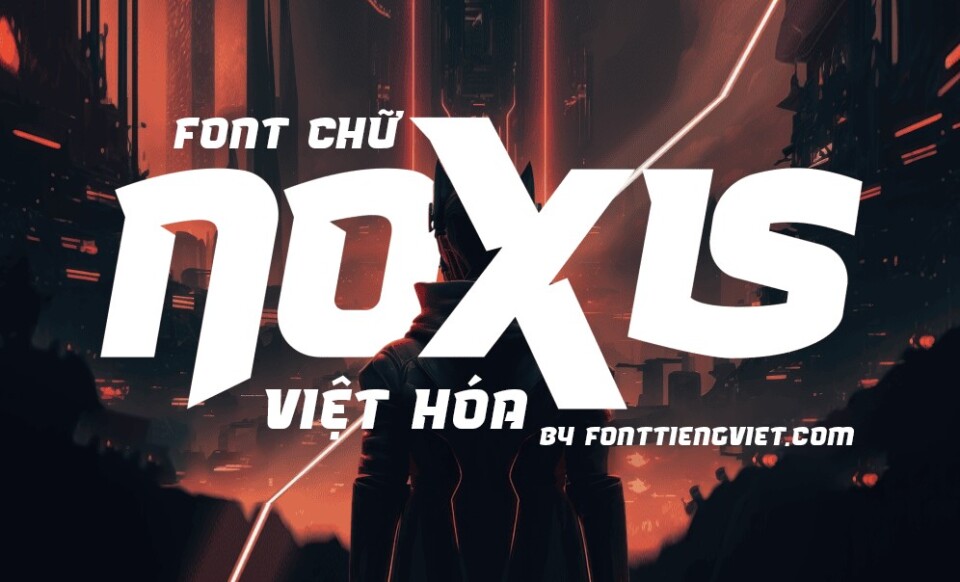
Font Việt hóa 1FTV Noxis
Giới thiệu bộ Font Việt hóa 1FTV Noxis đầy ấn tượng
Trong thế giới đồ họa hiện đại, việc tìm kiếm một Font Miễn Phí chất lượng và hỗ trợ tiếng Việt đầy đủ luôn là ưu tiên hàng đầu của các bạn học sinh cũng như giáo viên. Font Việt hóa 1FTV Noxis nổi lên như một sự lựa chọn hoàn hảo nhờ phong cách thiết kế mạnh mẽ, hiện đại và vô cùng chuyên nghiệp. Đây là bộ font mang hơi hướng tương lai, giúp các bài thuyết trình hay ấn phẩm truyền thông của nhà trường trở nên thu hút và dễ tiếp cận hơn với người xem ngay từ cái nhìn đầu tiên.
Đặc điểm nổi bật của Font Việt hóa 1FTV Noxis
Thiết kế tối giản và hiện đại
Font Việt hóa 1FTV Noxis sở hữu những đường nét thanh thoát nhưng không kém phần dứt khoát. Cấu trúc chữ được tối ưu hóa để giữ được độ sắc nét khi hiển thị trên cả màn hình kỹ thuật số lẫn bản in. Điều này giúp các em học sinh dễ dàng sử dụng trong việc thiết kế poster câu lạc bộ hoặc làm bìa tiểu luận. Khả năng hiển thị rõ ràng của bộ font này cũng giúp thầy cô soạn thảo giáo án điện tử một cách sinh động, tạo cảm hứng học tập cho học sinh.
Khả năng ứng dụng linh hoạt
Điểm cộng lớn nhất của Font Việt hóa 1FTV Noxis chính là sự linh hoạt. Bạn có thể sử dụng font này cho các tiêu đề lớn cần sự nổi bật hoặc các đoạn văn bản ngắn yêu cầu tính thẩm mỹ cao. Với bộ mã Unicode chuẩn, việc gõ tiếng Việt có dấu hoàn toàn không xảy ra lỗi hiển thị, đảm bảo tính chuyên nghiệp tuyệt đối cho mọi sản phẩm thiết kế trong môi trường giáo dục.
Kết luận về bộ font chất lượng này